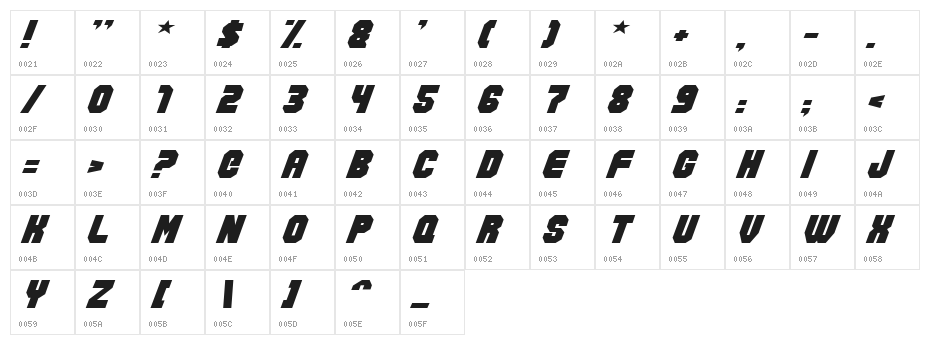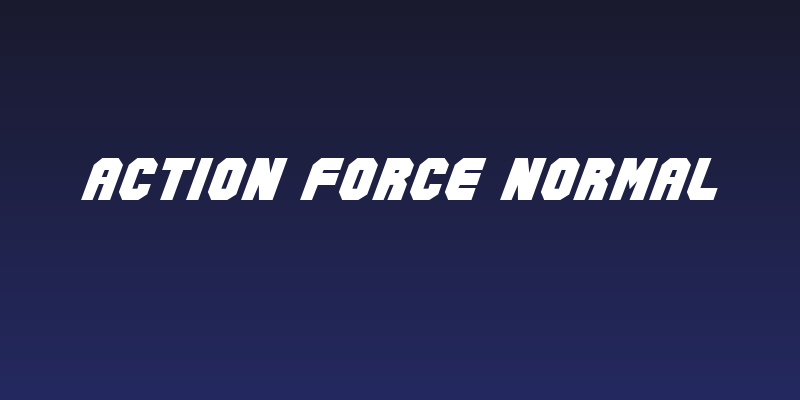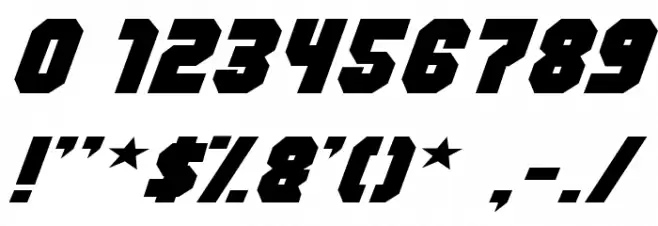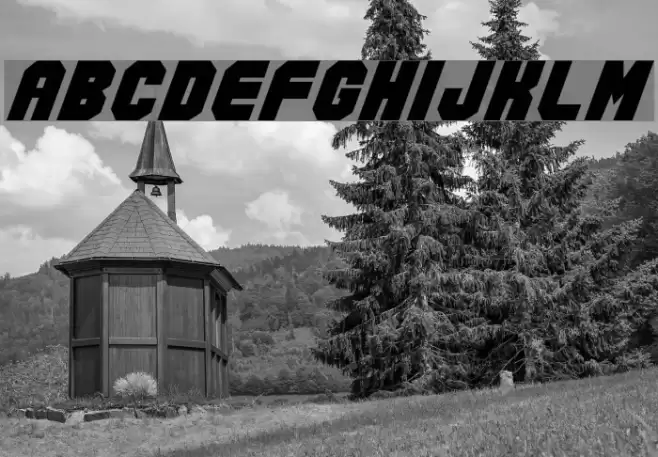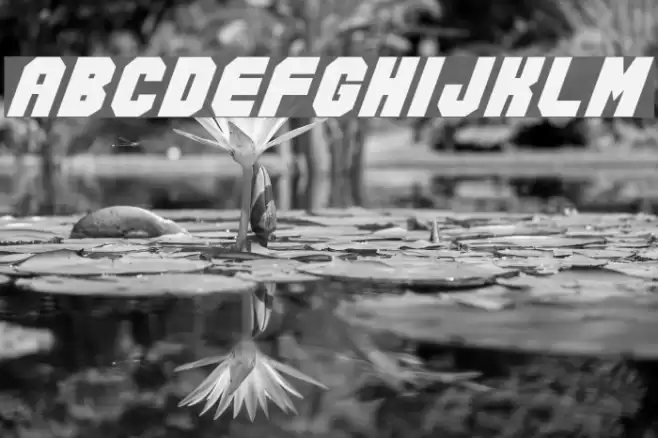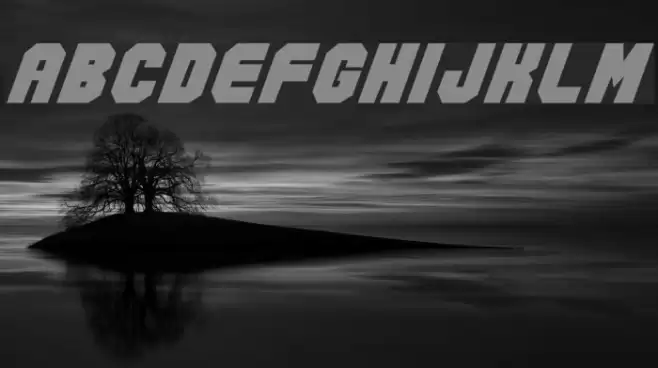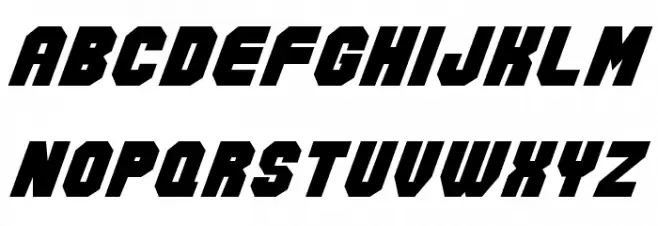
Action Force Normal Font
| Vorgeschlagene Projekte | Ideal for sports branding, action-themed posters, video game titles, and dynamic advertising campaigns. |